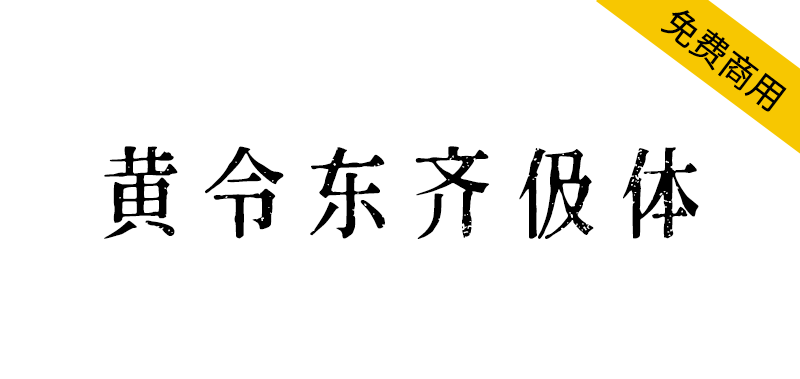
黄令东齐伋体(QIJIFALLBACK),一款可以媲美康熙字典体的免费商用字体,摘自明代木版印刷书籍《凌閔刻本》,采用半自动计算机视觉和OCR制作而成的一款字体。基本思源宋体改造而来,对中文汉字支持极佳,无论是简体还是繁体都基本上不缺字!
黄令东齐伋体,笔画风格书法特征浓郁,比常规的明朝体更具韵律感,富有人文气息。黄令东齐伋体非常适宜用于需要展现人文感、手作感、古拙感的场景。